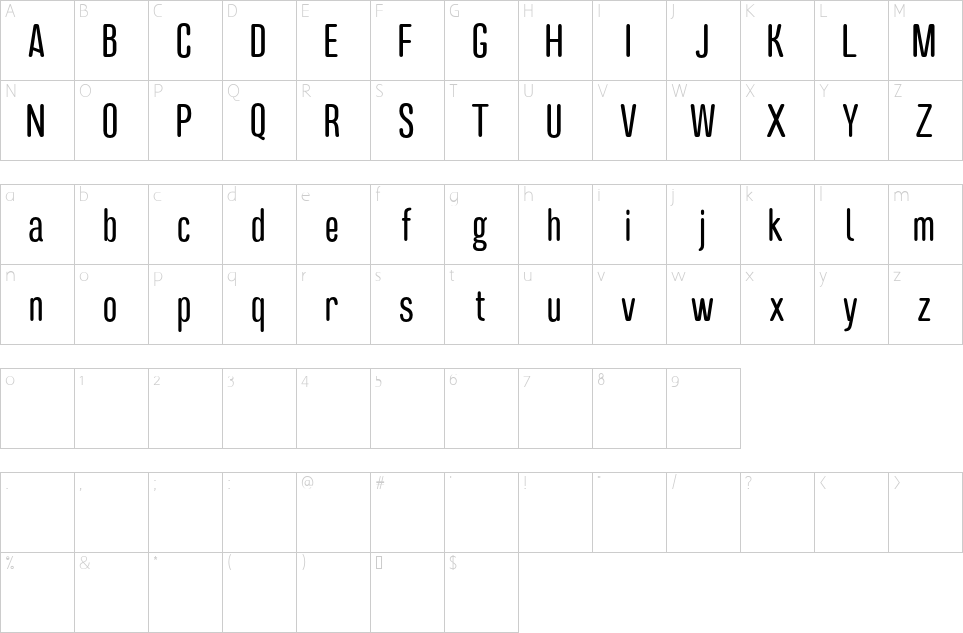
Descubra Dozed Rounded Font, uma elegante fonte gráfica feita para dar um toque sofisticado a seus projetos digitais. Desenvolvida por Craft Supply Co, esta fonte é perfeitamente adaptada para uso em sistemas Windows e Mac, oferecendo você mais opções de personalização nos seus materiais impressos ou digitais. Com seu design arredondado e moderno, Dozed Rounded adiciona um toque de sofistica à sua escrita digital. A sua utilização é fácil, tanto no ambiente do computador quanto na versão para dispositivos móveis. Com o download gratuito disponível, você tem a oportunidade de adicionar esta fonte à sua coleção e experimentar os benefícios que ela oferece. Dozed Rounded é mais do que uma fonte; é um recurso gráfico que pode dar uma nova vida às suas criações. Seja para cartões de festa, materiais escolares ou qualquer outro projeto onde desejar um toque especial na aparência final dos seus escritos, Dozed Rounded está aqui para ajudar.